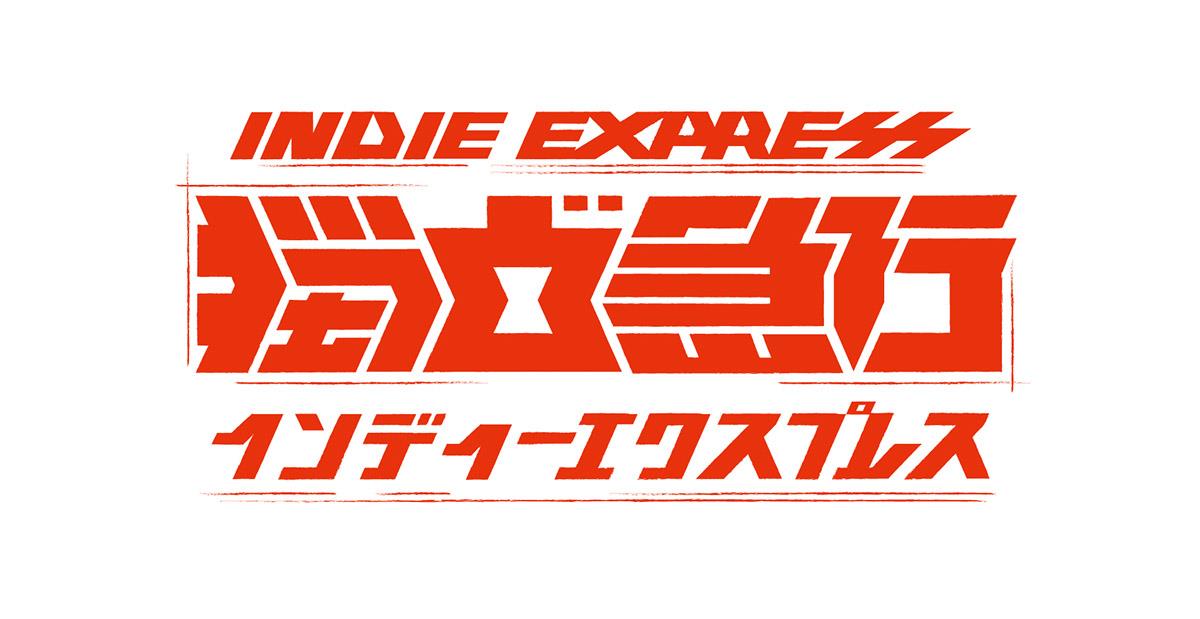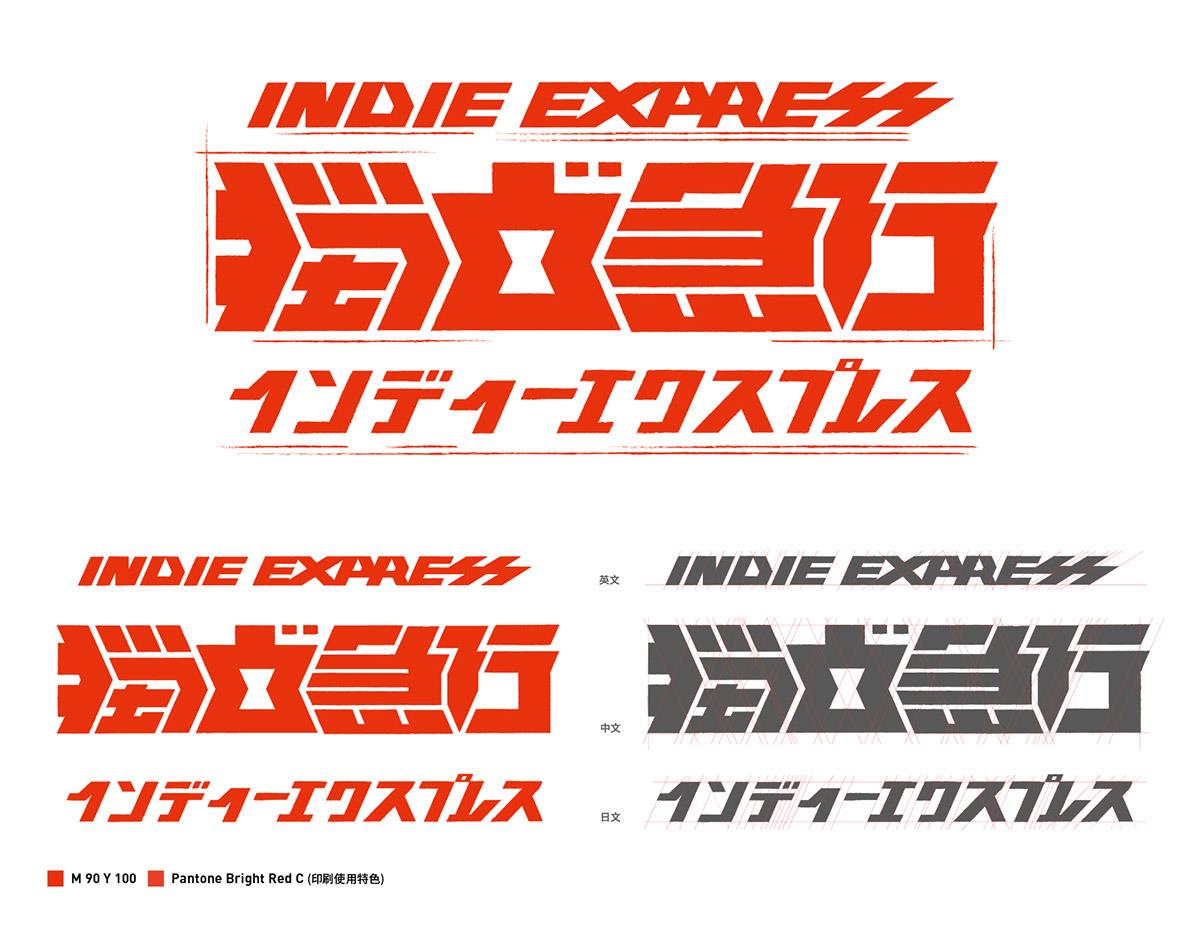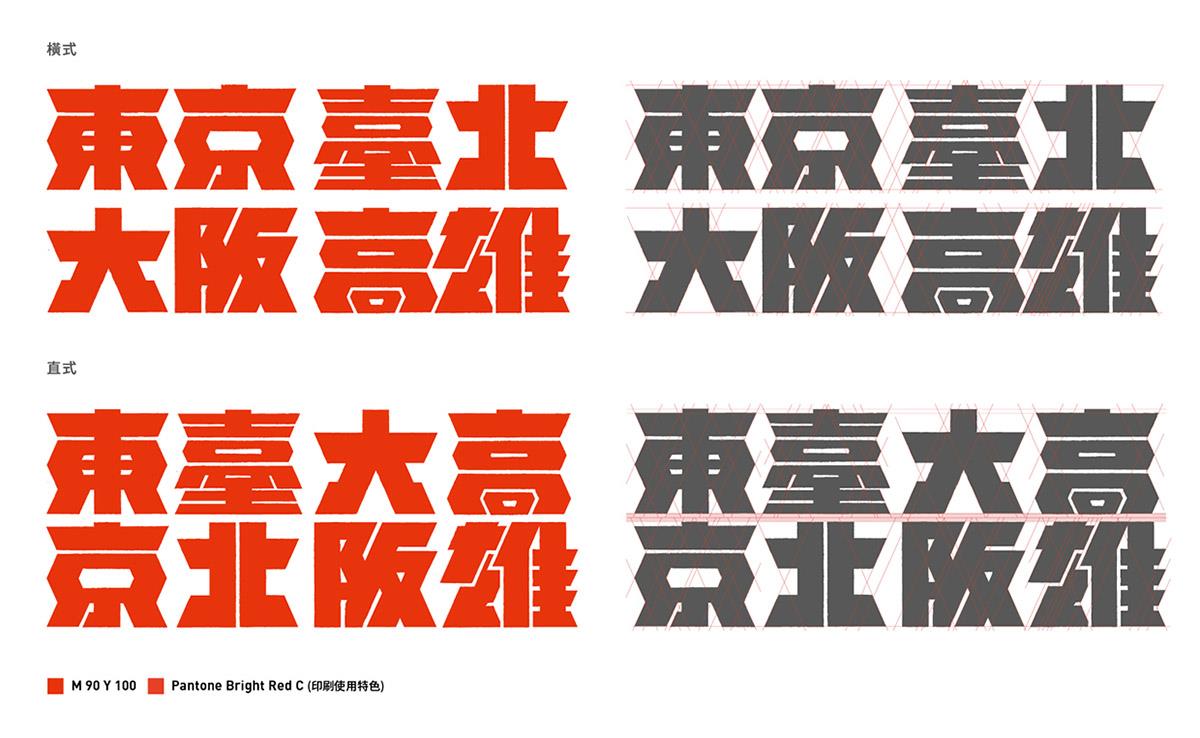
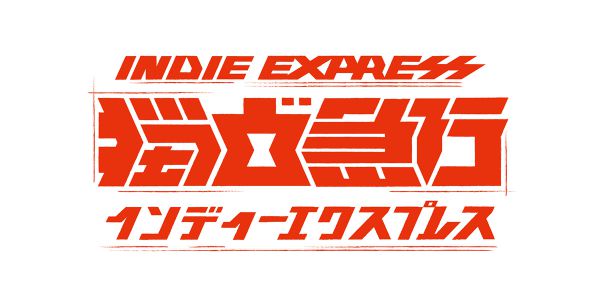
独立急行展视觉形象设计
台北–东京间的独立音乐快速直达车 | Indie Express between Taipei and Tokyo
东京与台北,不管在文化背景、地理位置以及时空距离都十分相近。台北、东京往返的时间也约莫仅等于在日本当地搭乘急行新干线往返东京、大阪之间的距离。作为两个亚洲独立音乐发达的城市,此次企划希望藉由「Indie Express」独立音乐特急列车的意象,将台湾/日本在地的新锐乐团以「特快急行」的方式推荐给在地乐迷,将最新颖、最独具时下代表性的日本/台湾独立摇滚乐团以最快速送达到各地乐迷的手中。(最初设定日本方面以东京为代表,后改为大阪为主)
主视觉设计概念 | Visual Design Concept
出发/穿梭/抵达 | Departure/Journey/Destination
根据本次企划概念,将急行特快车作为音乐传达的媒介,主视觉设计,我们将音乐的传达与交流以空间穿梭的概念呈现。声音/音乐的传达是透过声波,而轨道是无形的,所传递的是感知上与精神上的作用,直达的目的地即是听者的内心。视觉设计上将实际的空间转换为较抽象的空间,透过独立急行的特快车,让音乐在不断地穿梭中直达每个人的内心,藉此达到音乐文化上的交流。城市海报的视觉符号上,由于这次的活动策划由台北出发,三角形的概念是一个意识的型态,三角形的透视顶点如同延伸的路,延伸的尽头即为交流的目的地─日本,日本的象征符号以最显著的国旗符号代表,同时将星球的概念与圆形的符号做了链接,让观者对画面的感受多一点想象,整个视觉也可以说是对于抽象的音乐交流空间做出的另一种诠释。
标准字 | Typeface
气势/指引/粗矿|Power/Leader/Masculinit
标准字设计上,在文字的设计上加入指引与汇集的意向,希望透过独立急行的活动进入音乐交流的时空。字体选择粗犷有气势的特粗黑体为设计骨架,结合列车车厢紧密链接的特性,将字体的负空间紧密地扣在一起,配色上参考日本地铁特急/急行等列车使用显著之橘/赤红为文字配色。